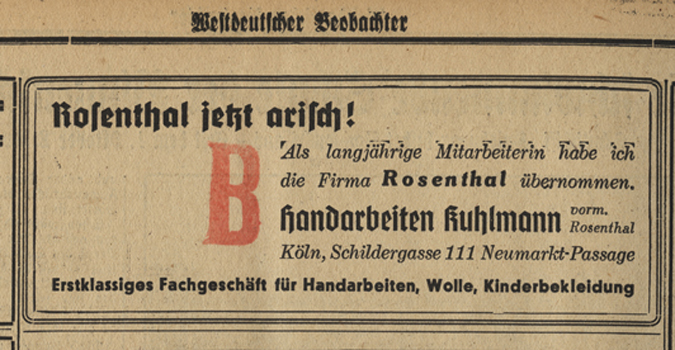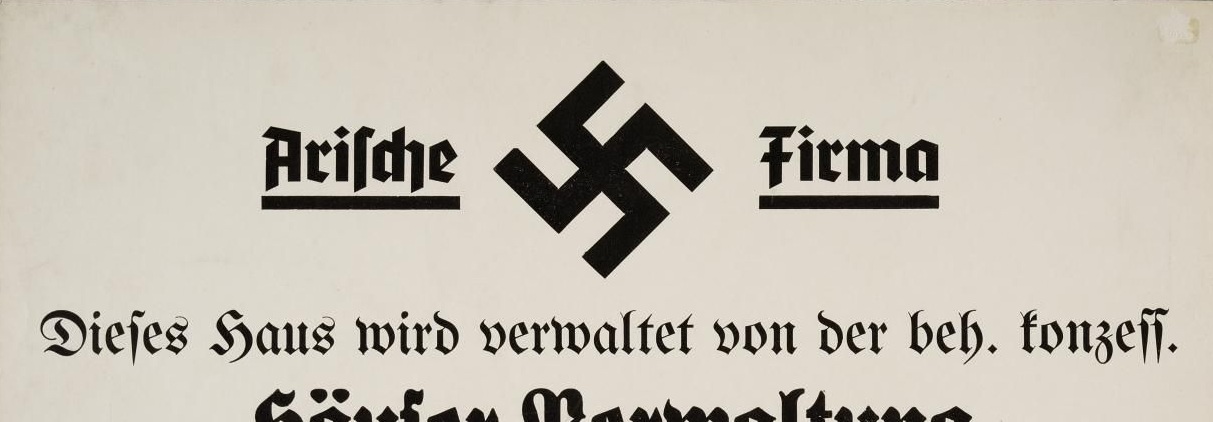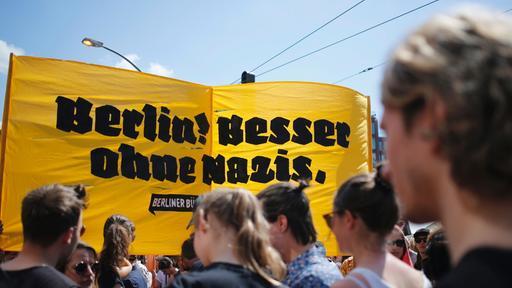
Schriftmuster Tannenberg
muss ich jetzt die Tannenberg verwenden um den Schaftstiefelgroteskschriften das Nazi-Image zu nehmen. Was für eine abstruse Ansicht.
Ich finde es komplett daneben Schriften aus der NS-Propaganda von dieser »losgelöst« zu verwenden – es gibt genügend historisch unbelastete.
Grundsätzlich sollte man sich informieren, was man so einsetzt und mit welchem Bildmaterial, Farbcodes man arbeitet usw. – das gilt nicht nur für Frakturschriften, sondern in der generellen Formensprache
Die Tannenberg habe ich übrigens schon verwendet.
Du wiederholst nur, du argumentierst nicht sauber für die Haltung, die du vertrittst und nicht gegen jene, die du ablehnst. Und gehst nicht auf die gestellten Fragen ein. Auch da machst du es dir zu einfach. … Man solle sich informieren. Das ist so banal, dass es kein Argument für gar nichts ist. Es gäbe ja unbelastete Alternativen. Da nimmst du die strittige Frage der Belastung vorweg. Ein Zirkelschluss-Argument. Wie wo warum welche Schriften belastet sind, ist Kern der Diskussion. Kennst du wirklich alle Schriften, die die Nazis einsetzen und vermeidest sie alle? Hast du das wirklich auch nur Ansatzweise geprüft? Und prüfst du nur vermeintliche Nazi-Schriften oder welche Herrscher, Regime und Regierungen, die irgendwo irgendwem Leid brachten, stehen da so auf deiner Abschussliste? Das müsstest du schon genauer erklären. Und so weiter und so fort. Einfach nur einzuwerfen, was man in dieser Frage tun solle oder nicht, was du abstrus findest oder nicht, ist zu wenig. Du darfst gern zu deiner Meinung stehen. Wenn wir ihr aber irgendeinen Wert bemessen sollen oder sie sogar überzeugend finden sollen, braucht es weit mehr als alles, was du bislang vorgetragen hast.
ich weiß es nicht – ich hatte noch nicht das Bedürfnis diese einzusetzen (bis auf damals die Tannenberg – da hab ich aber bewusst diese verwendet). Es geht mir auch nicht nur um Grotesk-Gotische sondern um Frakturen allgemein.
Da kann man sehr schnell in historischem Kontext ins Klo greifen – nicht nur in Verbindung mit NS.
Ich würde mich auf jeden Fall im Vorfeld schlau machen – »zweifelsfreie« kann ich aktuell nicht nennen, weil die Sache bisher außerhalb meines Anwendungsgebiets nicht aber meines Wahrnehmungsgebiets liegt.
evtl. wärs ja interessant, wenn wir unsere Energie mal in die Suche nach einer unbelasteten »Schaftstiefelgrotesk« zu stecken anstatt Beispiele zu suchen in denen die Tannenberg nicht im direkten NS-Kontext steht.
Mir gehts auch nicht darum herauszufinden, wo die SSG in den 30er/40er Jahren in nicht NS-Kontext eingesetzt wurden – es ist einfach zu viel NS-Image mit den SSG und deren Formensprache verknüpft.
Sich informieren heißt aber nicht, sich die Informationen, die zu meiner Meinung passen heraus zu picken  :tuschel:
danke Martin für die Rückmeldung – ich frag mich halt auch zusätzlich zu welchem Zweck man so eine Schrift einsetzen sollte. Nur weil es sie gibt ? Bewusst die zweifelhafte Assoziation in Kauf nehmen ?
ich frag mich halt auch zusätzlich zu welchem Zweck man so eine Schrift einsetzen sollte
Hatten wir schon, aber mal zwei Gründe:
- sie ist schön (...de gustibus...)
- sie ist die lesbarste unter den Gebrochenen
Wahrscheinlich ist dieses Forum einer der sehr wenigen Orte, an dem drei Leute diese Schriften schön nennen. In der Literatur, abseits des Internets, wird man diese Auffassung kaum finden. Textlektüre dürfte auch deshalb auf Dauer hart für den Leser werden. Vielleicht vergleichbar mit Texten aus Helvetica. Die DDR-Verlage, die keine so großen Vorbehalte gegen gebrochene Schriften hatten wie die westdeutschen, haben auch die Fraktur nicht gewöhnte Leser mit schönen Schriften versorgt, also mit Fraktur, nicht mit alten oder neuen Gotischen. »Lesbar« ist sie vielleicht auf einem Bahnhofsschild, dort dann allerdings auch in Größe unschön.
evtl. wärs ja interessant, wenn wir unsere Energie mal in die Suche nach einer unbelasteten »Schaftstiefelgrotesk« zu stecken anstatt Beispiele zu suchen in denen die Tannenberg nicht im direkten NS-Kontext steht.
Ich denke, die meisten Leute assoziieren nun mal die Schaftstiefelgrotesken mit den Nazis. Diese Assoziation können wir nicht aus der Welt reden.
Im weiteren Sinn gibt es zwar auch andere Grotesk-Gotische, nämlich gebrochene Jugendstilschriften (hier im Thread glaubs schon verschiedentlich gezeigt – jüngst etwa auf der Teigwaren-Verpackung). Sie sind ansatzweise geometrisch und haben (relativ) gleichschwere Linien. Allerdings fehlt das Gestaltungselement der Schaftstiefel – man kann sie also nicht zu den eigentlichen Schaftstiefelgrotesken zählen. Folglich dürfte die Assoziierung mit den Nazis bei solchen Schriften kaum stärker sein als bei den Gebrochenen insgesamt.
Hatten wir schon, aber mal zwei Gründe:
- sie ist schön (...de gustibus...)
- sie ist die lesbarste unter den Gebrochenen
Da haben wir doch gleich zwei besonders «schöne» und «lesbarste» Beispiele:
:-)
Ein aktueller Einsatz braucht für mich eine Begründung – eine Verwendung in einer Speisekarte finde ich daneben – da hätte man sicherlich etwas unbelastetes gefunden. (In die Kneipe würde ich schonmal gar nicht reingehen – würde mich immer noch interessieren, welche Kneipe das war.)
wow. ich find die einstellung von dir schon heftig verbohrt. du würdest in die kneipe nicht gehen, weil die eine schriftart aus ns-zeiten verwenden welche in keinem verbindung zur damaligen geschichte steht sondern vollkommen losgelößt und anders eingesetzt verwendet wurde?
Im Fall der in Rede stehenden Schriften ist es jedoch weitestgehend andersherum: erst war die Etablierung einer bestimmten Verrohung der Sprache in der deutschen Politik nach dem Ersten Weltkrieg, dann die gewisse «Bewegung», und erst dann sind diese Schriften richtig in Schwung gekommen.